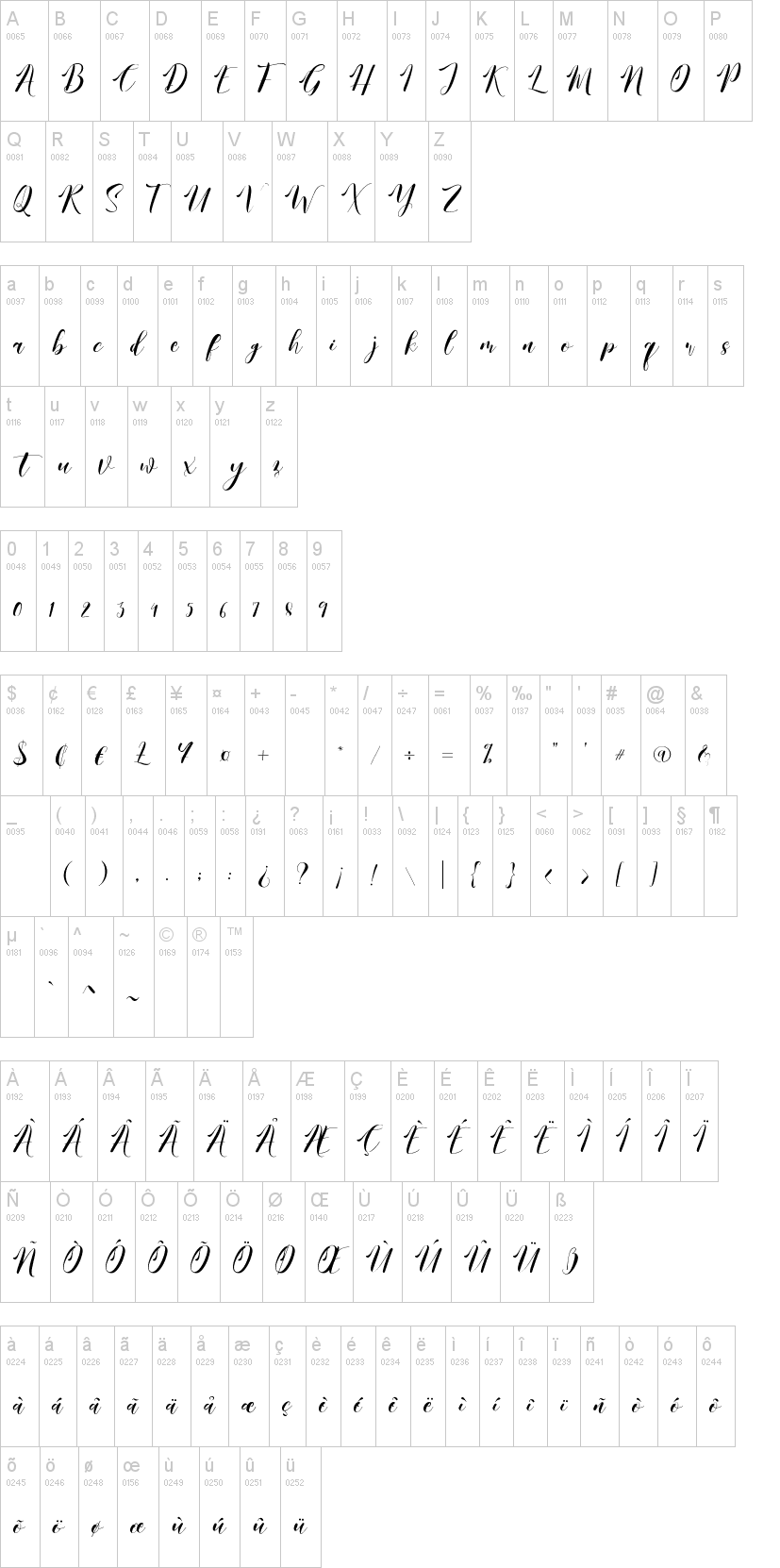
Jealousy
Jealousy 字体是一款简约优雅的英文字体,它的设计灵感来自于经典的欧罗巴风格,具有极强的视觉冲击力,非常适合用于海报、标志以及其他印刷品的设计上。它的字形设计精细,笔画清晰,拥有独特的美感,使得它在英文字体中独树一帜。Jealousy字体有着清新的外观,可以满足不同的设计需求,是一款很受欢迎的英文字体。
Jealousy是一款非常不错的手写艺术字体,具有很好的视觉感,适合于文化类的宣传设计、商业类品牌的广告和产品包装设计以及个性化文字排版等较多场景。
Jealousy字符映射图